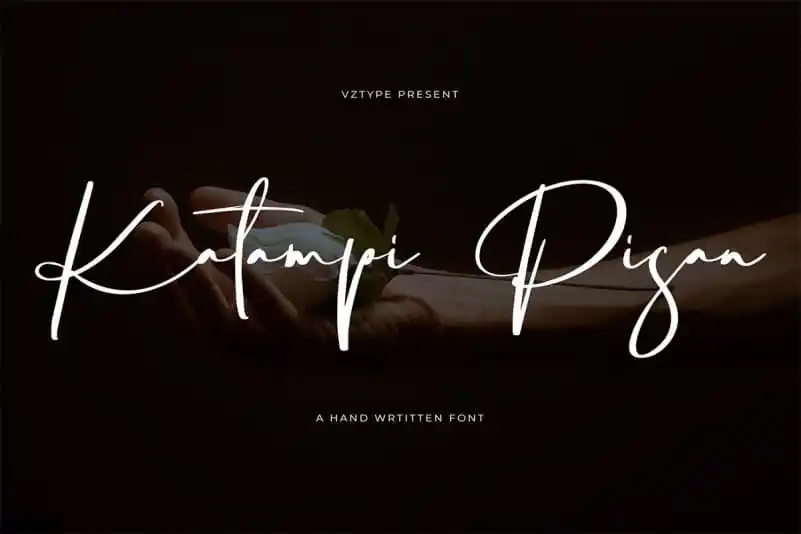
Katampi pisan Handwritten Font – Download Grátis
Katampi pisan é uma fonte escrita a mão que oferece um toque criativo e único para projetos variados, especialmente adequada para designers dedicados a manuscritos e arte personalizada. Esta fonte vem equipada com caracteres básicos e traz os traços de um pincel divertido, garantindo harmonia e perfeição entre todos os elementos da composição. Katampi pisan é perfeito para t-shirts customizadas, citações, etiquetas, embalagens, logotipos ou escrita longa. Para aprimorar ainda mais sua experiência com esta fonte, incluímos kerning e matrizes personalizados que se adaptam às suas necessidades específicas. Katampi pisan é uma opção ideal para quem deseja adicionar um toque único e criativo em seus projetos gráficos. Com uma abrangência tão ampla de aplicações, a fonte será certamente uma ótima escolha para os designers que procuram algo autêntico para aquecer suas criações.